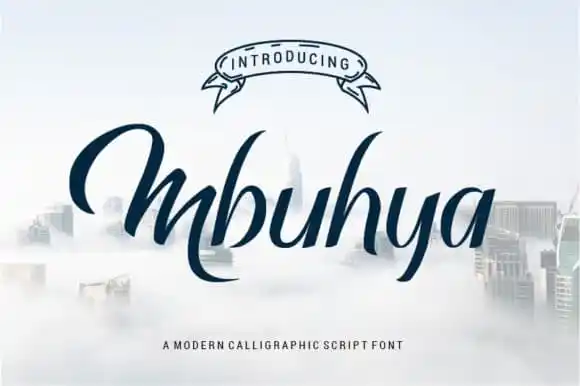
Mbuhya Script Font é uma fonte elegante criada pela Smart Studio, apresentando uma aparência natural e fresca que se assemelha a letra feita à mão. Ela possui um estilo moderno de caligrafia, oferecendo versatilidade para criar design impressionantes, especialmente em invitações de casamento, arte de cartão, postagens no média social e muito mais. Suas linhas fluidas e delicadas trazem a elegância e classe necessárias para qualquer projeto que você decida adicionar essa fonte à sua coleção. Nada melhor do que um belo estilo natural e moderno, combinado com o charme da caligrafia artística para criar algo único e impactante. Aproveite esse conjunto de recursos incrivelmente versátil de Smart Studio.